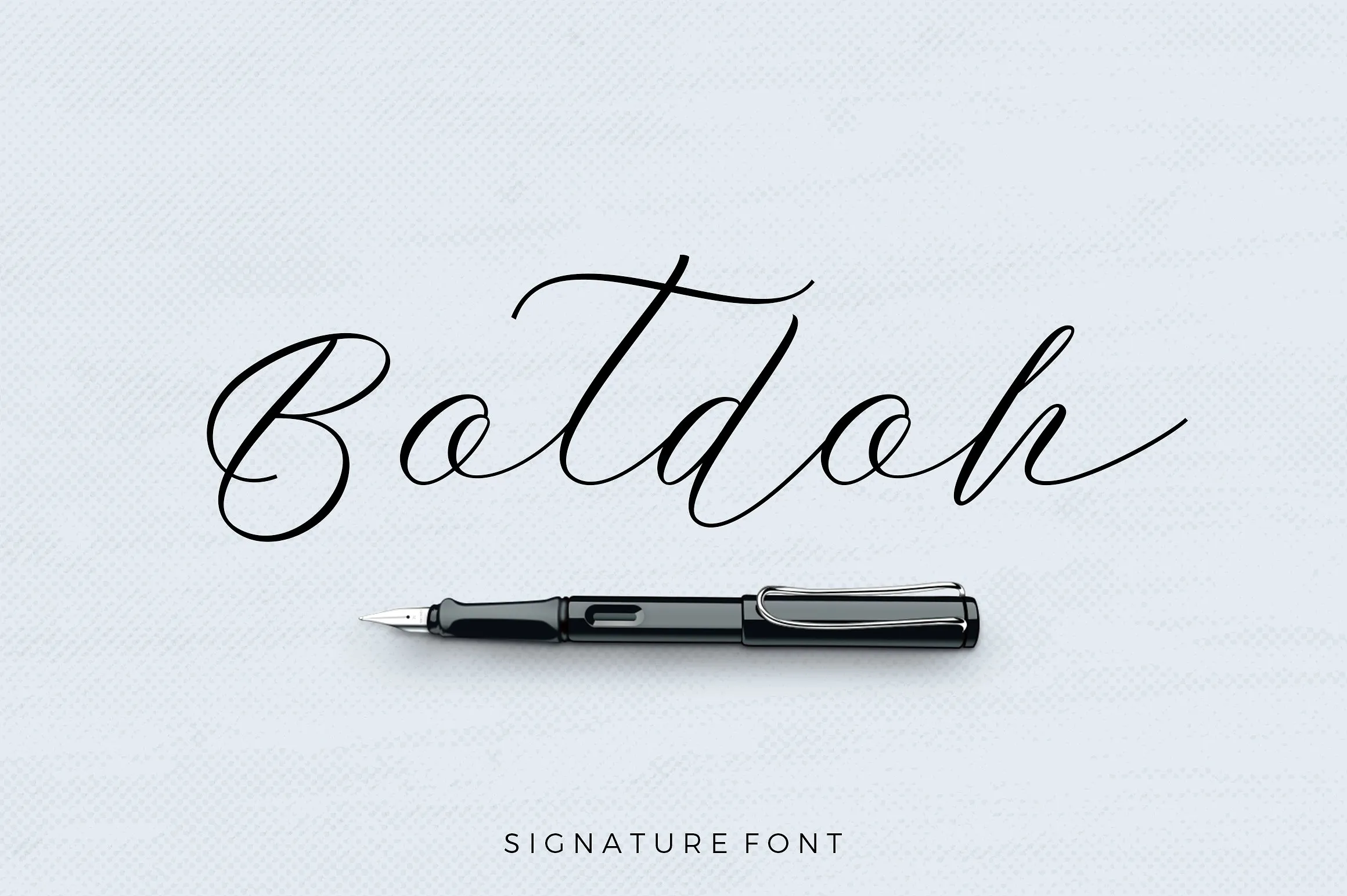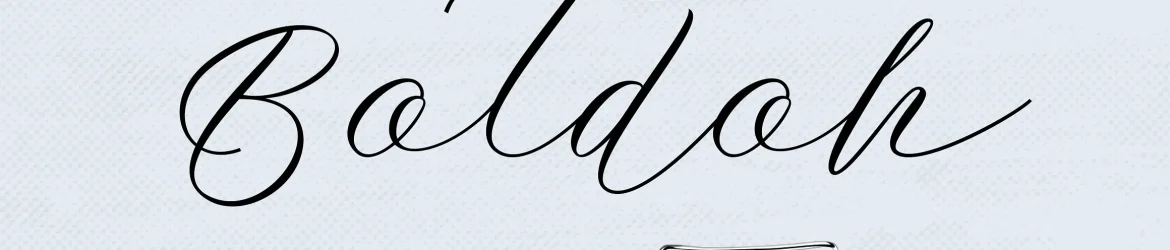
Botdoh Script Font – Download Grátis
Introduzimos a Botdoh Script Font! Ela foi criada pela Elementype, uma font premium que você pode encontrar na Creativemarket. Atualmente, está disponível gratuitamente para download. Esta font script é perfeita para fazer seu texto parecer belo e natural. Seu estilo assinado dá ao texto um toque mais autêntico e realista. Botdoh Script é ideal para uso em sua marca, citações escritas a mão, logotipos, cabeçalhos, posters, roupas e embalagens, business cards e muito mais. Experimente o botdoh script na sua próxima projeto de design!